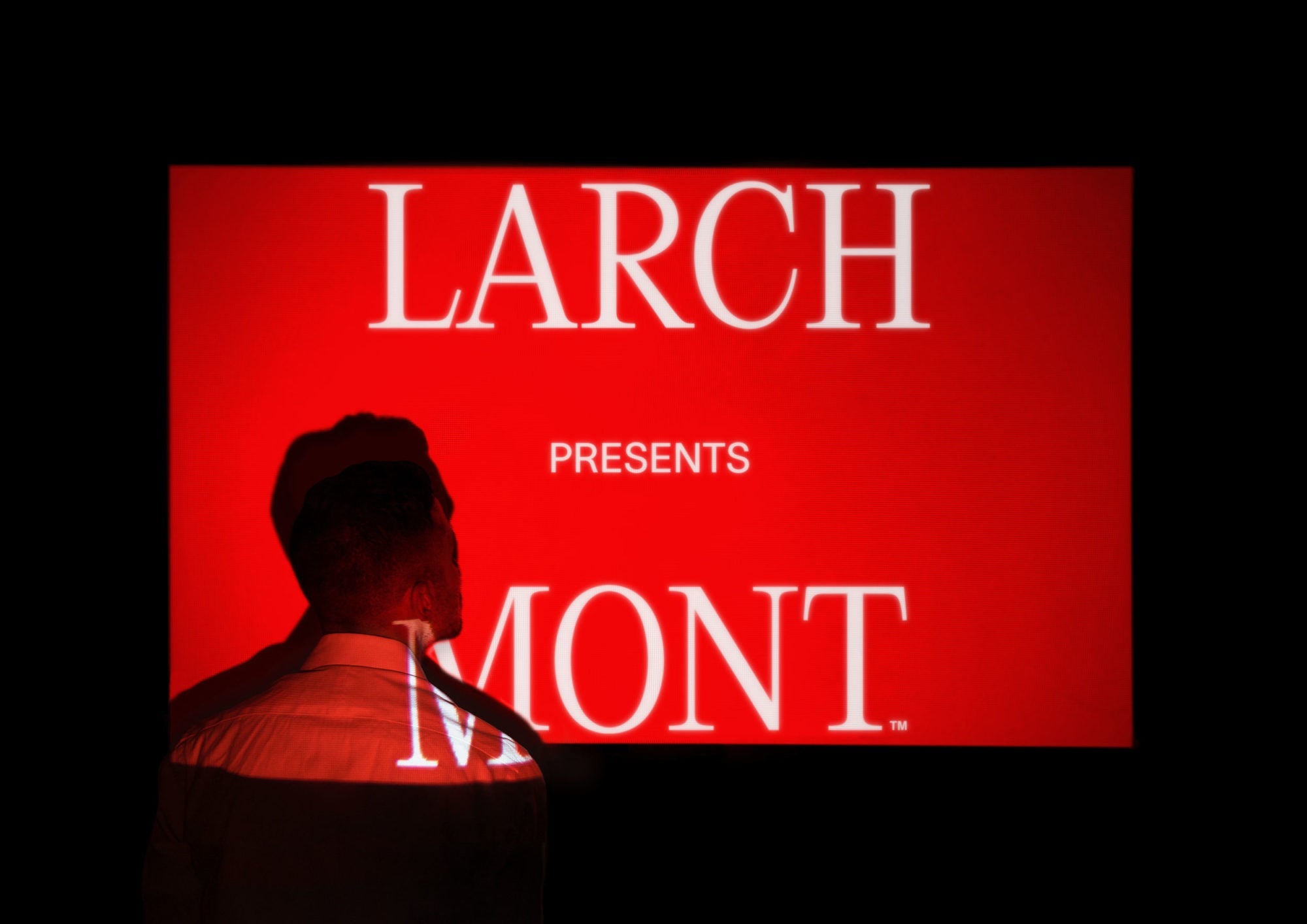
Larchmont est une société de production cinématographique indépendante fondée par le réalisateur Noah Marshall et l'associé directeur Ngaio McCreadie.
Larchmont est une équipe de six réalisateurs spécialisés dans différents aspects de la production cinématographique. L'entreprise est motivée par la création de films publicitaires uniques et de haute qualité, qui se démarquent sur le marché. Forte de son équipe de réalisateurs expérimentés et talentueux, Larchmont s'engage à proposer des histoires captivantes qui captivent et divertissent le public.
Notre idée et notre solution créative consistaient à célébrer le romantisme du cinéma et son histoire, en évoquant l'expérience et la nostalgie d'un grand film. La marque Larchmont souhaite se différencier sur le marché en créant une identité qui reflète ses valeurs et se démarque des autres acteurs culturels tels que la mode, l'architecture, les produits, la musique et le cinéma. Pour y parvenir, nous avons utilisé une police serif haut de gamme qui transmet un caractère cinématographique, artisanal et mystérieux. Célébrer la narration dans sa forme la plus simple et la plus puissante : une image et une phrase.
L'emprunt de vocabulaire à des films populaires a créé un ton unique et pertinent pour la marque. La police utilitaire sans empattement s'inspire des outils de réalisation cinématographique, tels que les boîtes de pellicule, les scripts et les documents de traitement. Elle séduit les agences de publicité, les producteurs en quête de partenaires et les réalisateurs souhaitant collaborer avec une société de production indépendante à l'identité intrigante.